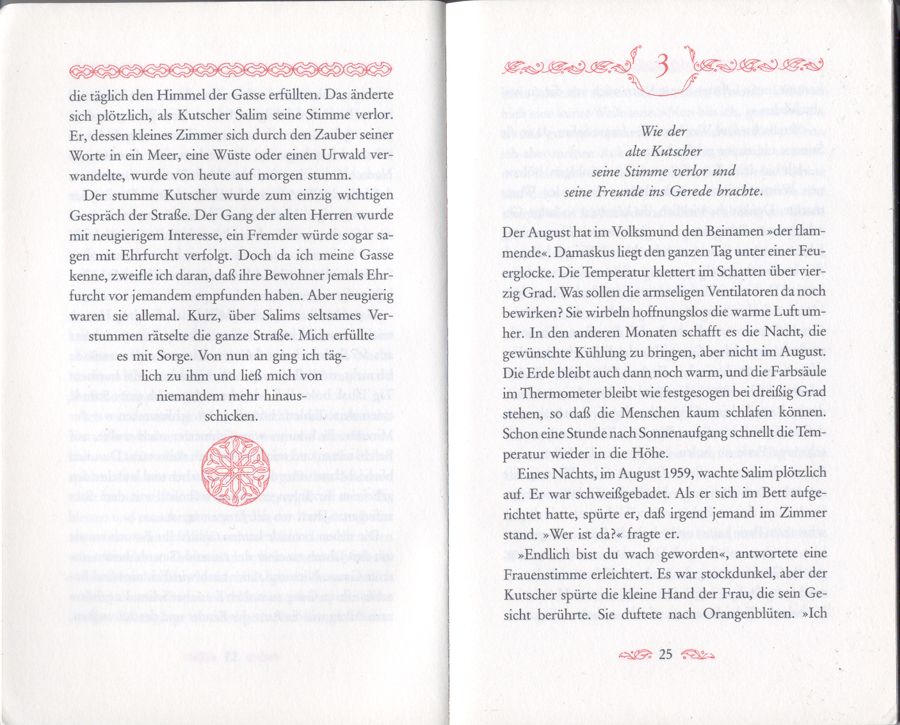
Beispiele Old Style und zweifarbig
ich bin auf der Suche nach Beispielen für ein Buchlayout, das folgende Komponenten aufweist:
1) Es soll zweifarbig sein, etwa indem alle Kapitelüberschriften rot gesetzt sind.
2) Es sollte eine ältere, klassische und stilvolle Anmutung vermitteln.
3) Dabei auch großzügige Ränder aufweisen, etwa durch die alte Regel Texthöhe = Papierbreite. (Der Punkt ist noch am unwichtigsten, die Sachen kann ich ja dann selbst herstellen)
Marion Zerbst / Werner Kafka
Das große Lexikon der Symbole
Zeichen / Schriften / Marken / Signale
Hg. von Prof. Dr. Rainer Dierkesmann
Leipzig: E.A. Seemann, 2003
Andreas Thalmayr [= Hans Magnus Enzensberger]
Lyrik nervt!
Erste Hilfe für gestreßte Leser
München / Wien: Carl Hanser, 2004
Und weil ich es gerade in den Fingern habe, dies nicht ganz passende Beispiel (es ist aber auch bloß eine Taschenbuchausgabe):
In Michael Endes Unendliche Geschichte sind einzelne Abschnitte einer Parallelhandlung in dunkelrot bzw. dunkelgrün gedruckt, bis sich der Leser ganz in die grüne Welt Phantasiens verliert.
Ich erinnere mich vage an florale Ornamente und eine schöne Schrift, habe das Buch aber nicht zur Hand (ist etwa 15 Jahre her). – Auch eine Möglichkeit Farbe zur Auszeichnung zu nutzen, wenn auch nicht traditionell.